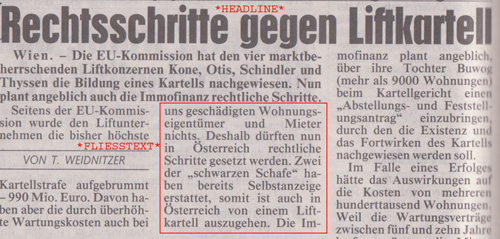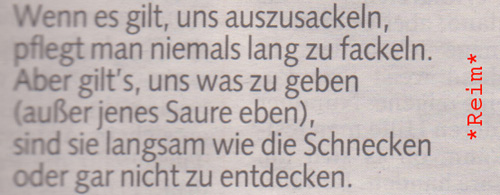
Suche Schrift von der Kronenzeitung
könnte mir jemand helfen, die Schriftart(en) der Kronenzeitung ausfindig zu machen? Das wäre sehr hilfreich...
Und zwar bräuchte ich die Schriftart der Headline, "Headline-Rot", Fließtext sowie die Schrift beim Reim.
falls noch jemand die Schriftart für die Headline kennt - das wäre genial.
ich gehe davon aus, dass der headline-font eine hausschrift ist.
ähnelt stark der placard condensed, die aber nicht fett genug ist. bevor jetzt jemand schreibt: »da gibt’s doch einen fetten schnitt.« ja, weiß ich, aber bei der placard bold condensed ist die übereinstimmung zur zeitungsschriftart leider nicht mehr ganz so groß.